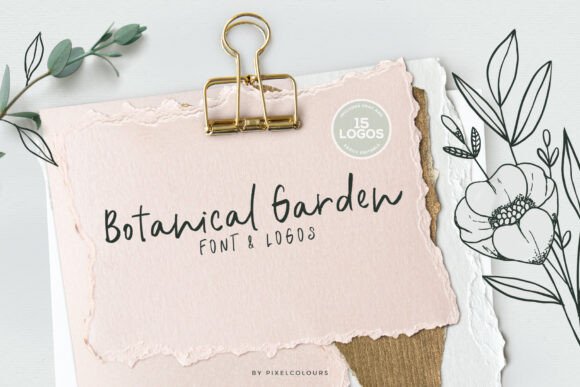
Botanical Garden
適切なデザイン要素を見つけるのは難しい場合がありますが、Botanical Garden は作品を即座に引き立てる優れたコレクションを提供します。
POD(オンデマンド印刷)製品、結婚式の招待状、またはソーシャルメディアのグラフィックを作成している場合でも、Botanical Garden は理想的です。